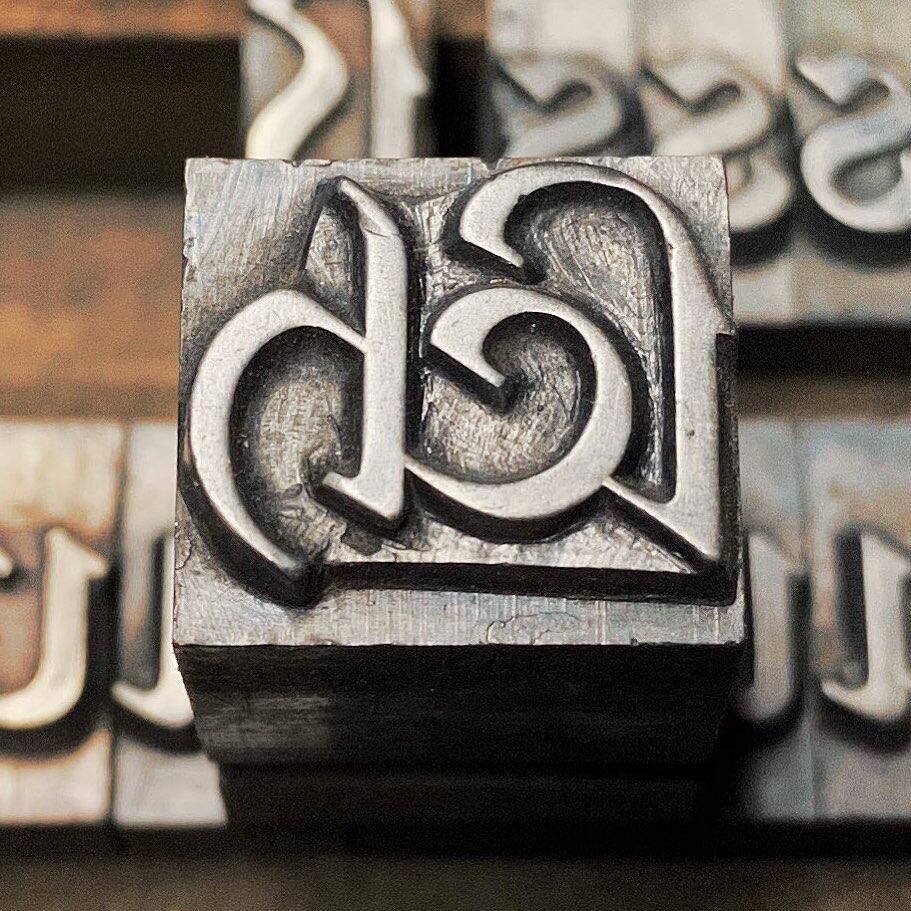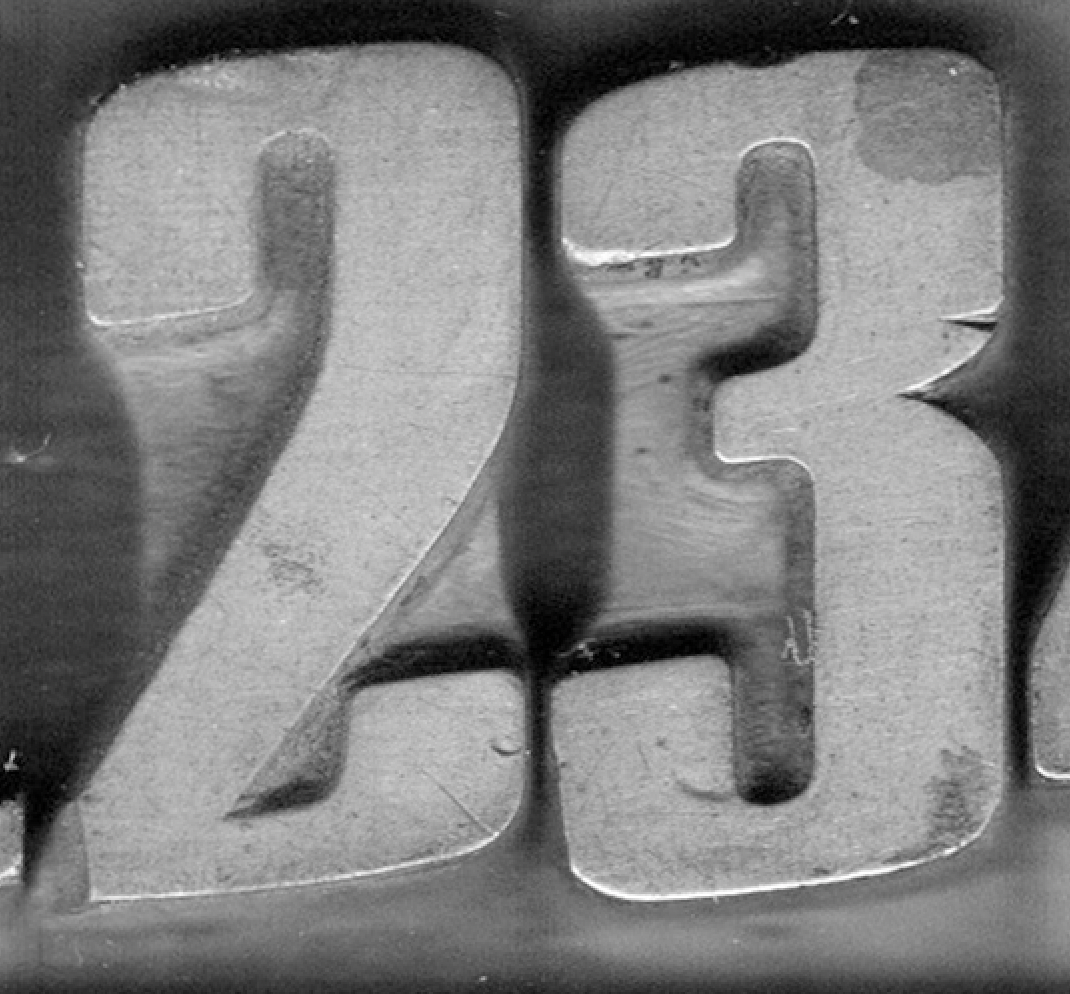
Suche hochauflösende Scans/Fotos von Bleilettern in versch. Abnutzungsstadien
Und zwar suche ich nach hochauflösenden Scans oder Fotos von Bleilettern. Genauer von der Gesicht Seite der Lettern.
Mir geht es dabei primär um die unterschiedlichen Abnutzungsstadien verschiedener Buchstaben. Was passiert mit der Serife, bricht vll ein Abstrich weg etc.
Warum ich das Suche?
Mein Vater – alter Schriftsetzermeister gelernt im Handsatz – ist vor wenigen Wochen plötzlich verstorben.
Ich habe nun so manche Idee im Kopf für "Tribut" Projekte die ein Mix aus Alt und Modern werden sollen.
Auch wenn ich es jetzt noch nicht schaffe mit der eigentlichen Arbeit loszulegen kann ich immerhin mit der Vorbereitung starten... Peux a peux, wie es mein Vater wohl auch gemacht hätte.
Was mir spontan einfallen würde um evtl. solche Aufnahmen/Referenzen zu bekommen:
Beim nächsten (Druck) Museum melden, anfragen.
Vielbenutzte Lettern sind irgendwann »abgenudelt«, das heißt, die eigentlich möglichst scharfe, physische Kante des Buchstabenbildes wird immer runder, was sich auch im Druck entsprechend widerspiegelt.
Daneben gibt es die punktuellen Schäden. Das besagte Wegbrechen von Haarlinien, Serifen, Kanten etc. sowie Eindellungen und Kratzer auf der Oberfläche. Zwei Beispiele unten.
Genau diese Veränderungen: das allgemeine "Abnudeln" wie du so schön sagst, zusammen mit den punktuellen Schäden (Kratzer, Macken, Bruch) ist genau die Patina, die ich Suche.
Diese ablesbare "Geschichte" der Lettern, der kontinuierliche Zahn der Zeit der an Allem nagt, die Spuren die unsere Taten hinterlassen ist genau das, was ich bei diesem Projekt "fühlen" möchte. Daher möchte ich das Ganze auch idealerweise auf echten Lettern aufbauen und sie nicht einfach selbst grafisch "nachbauen" und "altern".
Deine Beispielfotos gehen da schon in eine exzellente Richtung.